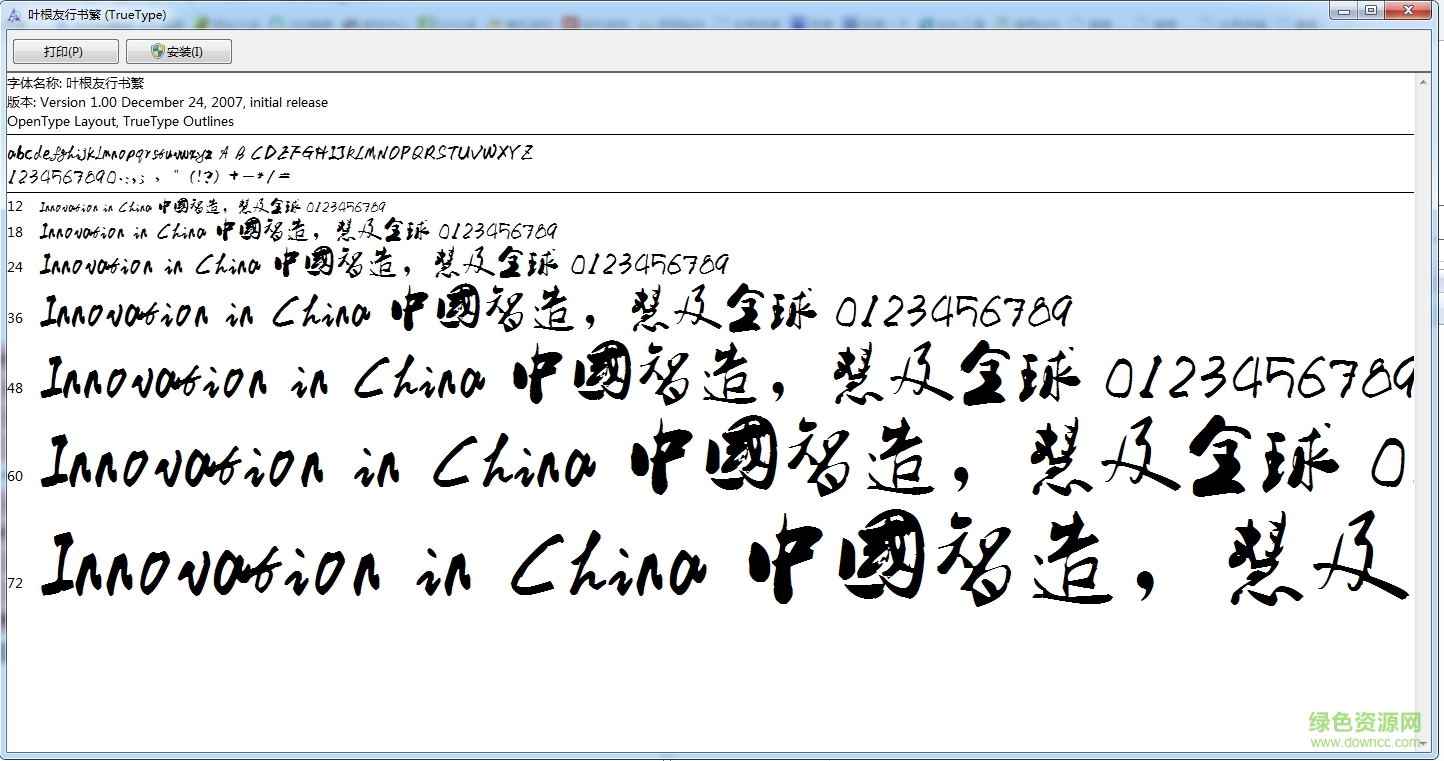
葉根友行書(shū)繁體是著名書(shū)法家葉根友的寫(xiě)作出的行書(shū)字體,字型放縱流動(dòng),筆毫的使轉(zhuǎn),讓字與字之間的相互牽連,非常優(yōu)美,可以當(dāng)做藝術(shù)字,也可當(dāng)做常規(guī)欣賞字體來(lái)使用。適用于網(wǎng)頁(yè)制作,平面設(shè)計(jì),寫(xiě)真,以及噴繪等。喜歡的小伙伴快來(lái)綠色資源網(wǎng)下載吧!